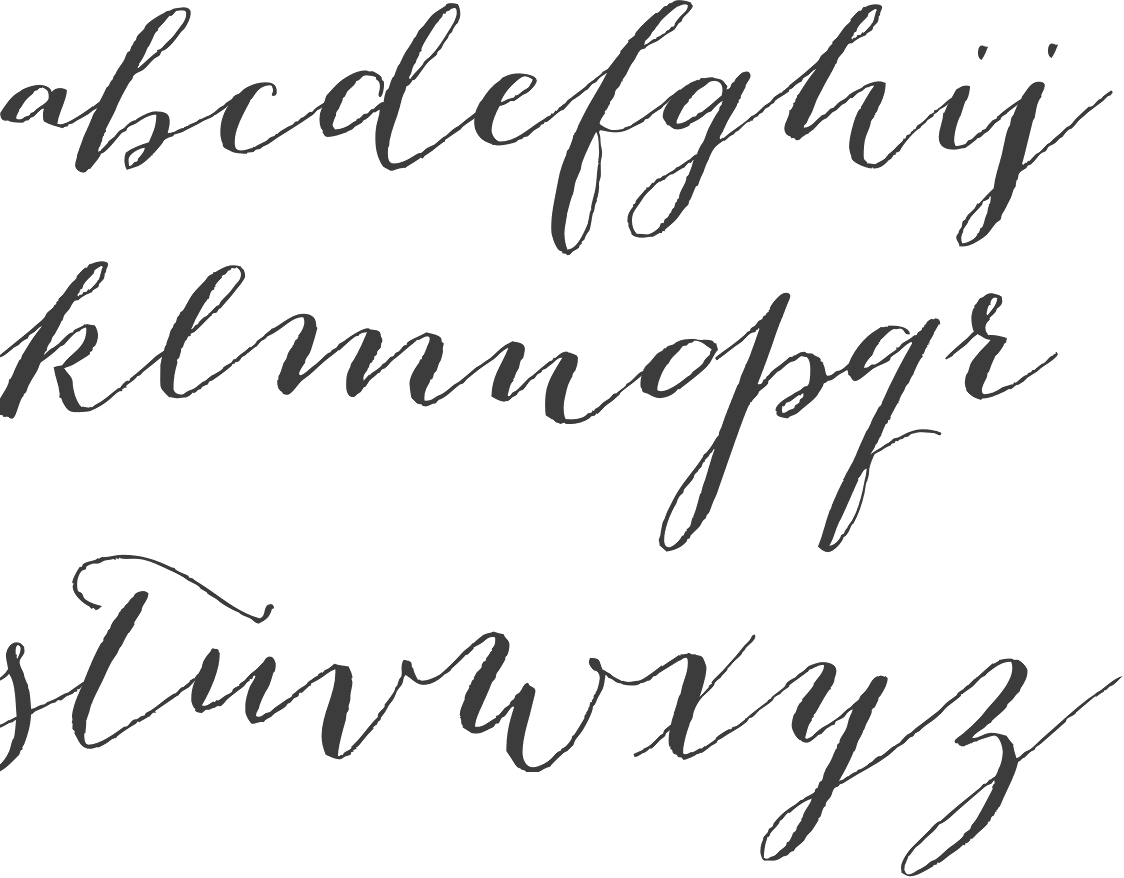
Изначально все писал для себя, исключительно для личного пользования, но решил, как вы поняли, запустить сайт для общего пользования. Сайт был создан буквально за 4 дня так что на нем могут присутствовать баги и недоработки.— Поддержка 8 шрифтов
— Каждое слово имеет свой уникальный наклон, расположение по вертикали и горизонтали
Рукописные шрифты.
Поскольку Instagram Stories предлагает некоторые возможности, когда мы пишем описания, комментарии или сообщения, нет возможности, кроме шрифта по умолчанию.
Тем не менее, есть сторонние инструменты которые предлагают пользователям возможность размещать другие источники. Продолжайте с нами, чтобы узнать больше об этой альтернативе и узнать, как используйте шрифты, которые делают ваши публикации более привлекательными, в данном случае рукописные шрифты.
Рукописные шрифты. Если вам нужно больше альтернатив для декорированного текста, просто нажмите «загрузить больше шрифтов». Параметры, которые появляются здесь, более случайны, немного отличаются от стандартных и смешивают ресурсы, у которых мало общего, смайлики и символы.
Отличие сайта в том, что на нем есть функция для создания самого шрифта. Щелкнув «Создай свой собственный шрифт»
Instagram и другие социальные сети создают шрифт, который лучше всего адаптируется к общему дизайну системы. Это часть согласованности, необходимой для визуальной простоты навигации по этим приложениям.
— Рукописные шрифты. Оказывается, есть способ добавить стилизованные буквы, которые на самом деле являются специальными символами, а также смайлики и другие символы.
На практике они выглядят как пользовательские шрифты, но технически называются Символы Юникода.
Поскольку этот совет все еще нов для многих, он
Поэтому некоторые классные приложения для этих шрифтов в Instagram можно настроить биографию профиля или выделите части подписей к фотографиям и видео, которые вы публикуете. Это творческие способы улучшить вашу стратегию цифрового маркетинга.
Помня, что эти источники следует использовать экономно, в основном для выделить важные части например, название вашей компании, специальные предложения по публикациям для получения выгоды от продаж, заголовок текста или раздела и т. д.
Рукописные шрифты. Какими бы забавными они ни были, чрезмерное их использование может создать впечатление, что ваша учетная запись слишком случайна.
Но используйте шрифты индивидуально сбалансированный стандартные шрифты хороши, если они разборчивы и эстетически соответствуют вашему бренду. Однако это очень важно для тех, кто использует Instagram в компаниях или влиятельных лицах.
Но с помощью этого пошагового плана мне удалось составить красивое письмо для моего друга. Приходите и приготовьтесь вместе с нами создать шедевр каллиграфии!
Все начинается с базы